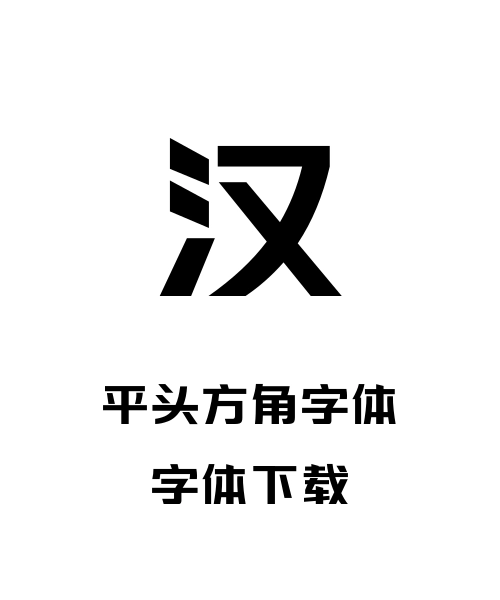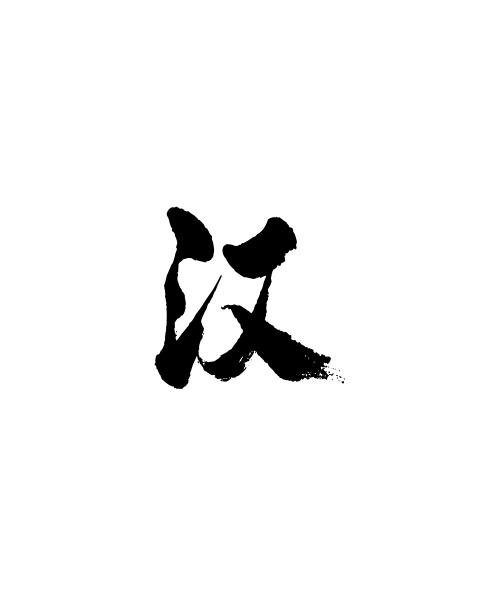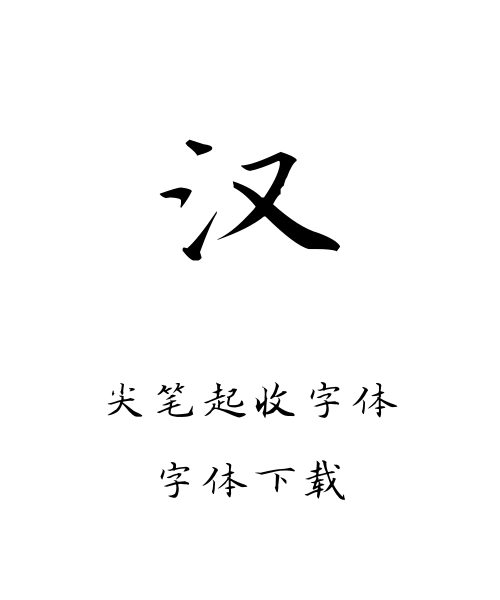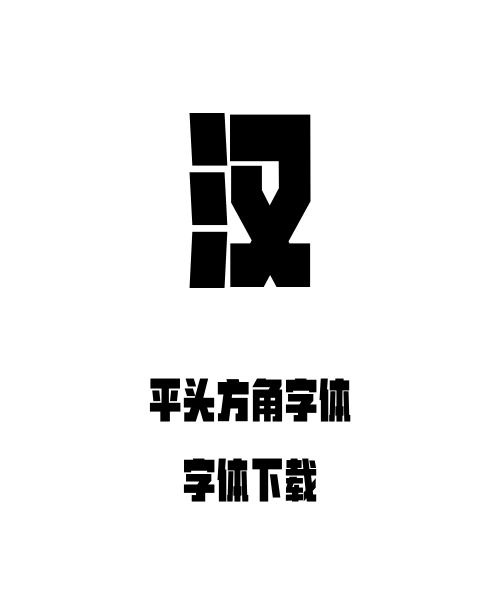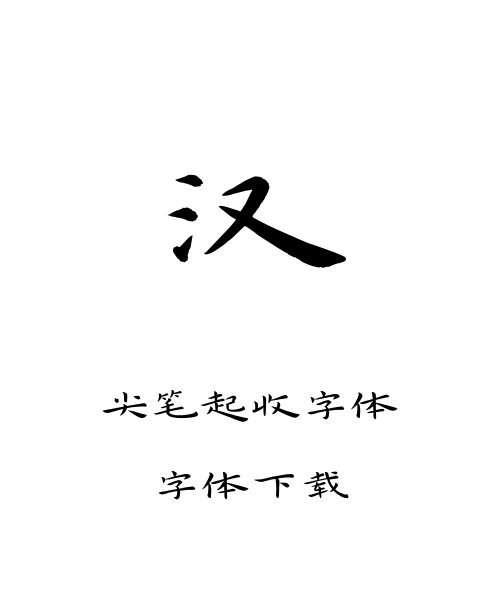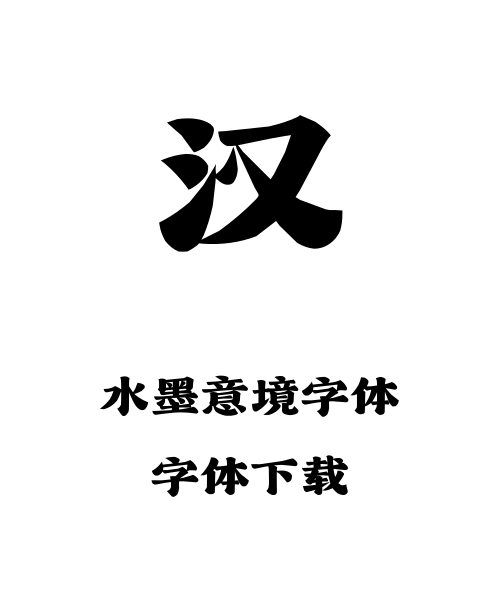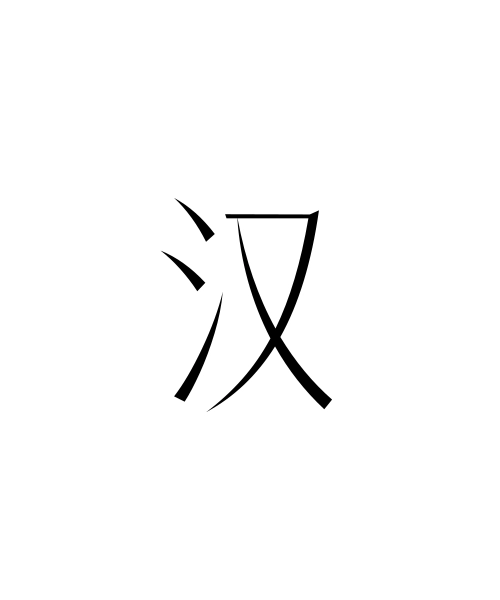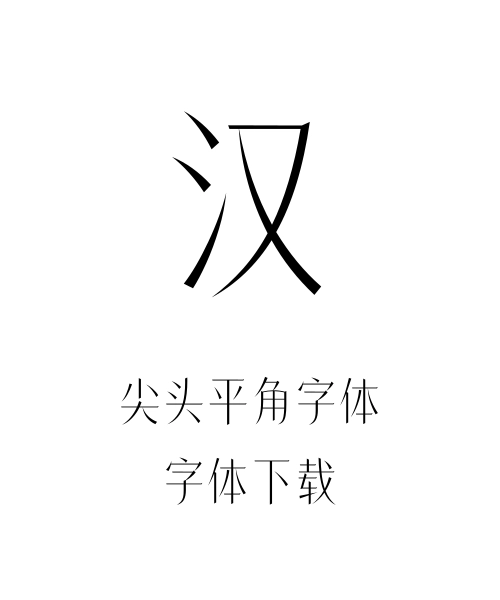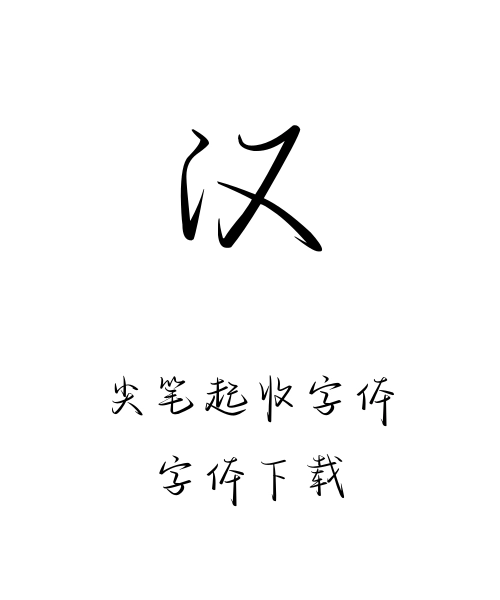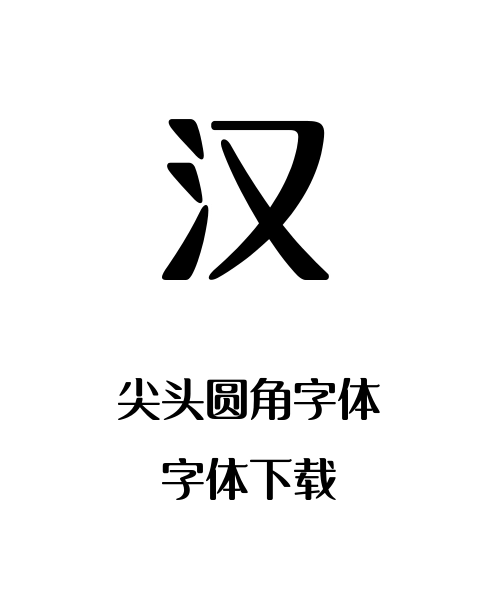
#音乐专辑封面字体合集 共6款
笔画带轻微弧线,结构舒展,字重550,适配专辑标题、歌手名,传递艺术流动感。
三极花朝体
上首水滴体
上首芊芊体
上首锐博体
上首韶华体
上首纤云体
#图书馆藏书标签字体合集 共6款
笔画纤细等宽,结构方正,字重300,适配书架分类标签、借阅卡,整齐有序便于检索。
汉标细黑体
上首简黑极细体
三极丽黑简体-细
三极正雅黑 纤细
Aa极细黑
青鸟华光简细黑1
#健身房器械标识字体合集 共6款
笔画硬朗方角,加粗至字重750,结构紧凑,适配器械使用说明、安全警示,清晰指引操作。
上首星芒体
上首力方体
上首正雅体
上首黑风体
三极黑金简体
三极力量酷黑
#儿童科普读物字体合集 共6款
笔画短粗圆角,结构饱满,字重450,适配科普绘本内页、少儿百科,亲和力强且易认。
上首悠然体
Aa维她柠檬茶
也字工厂润圆体
上首纯元体
上首团圆体
郑庆科奈奈圆
#企业年报封面字体合集 共6款
笔画粗细分明,结构严谨无装饰,字重700,适配年报封面标题、财务摘要,强化专业信赖感。
三极罗丽黑简体-粗
三极团结体 粗
三极正雅黑 常规
汉标炫粗黑体
Aa奇思细黑体
青鸟华光简黑体
#婚礼请柬标题字体合集 共6款
笔画圆润饱满,结构扁宽,字重600,适配请柬主标题、婚宴桌卡,传递温馨浪漫感。
上首夏木体
上首悦圆体
文道瘦圆体
Aa清欢圆体
Aa汤圆体